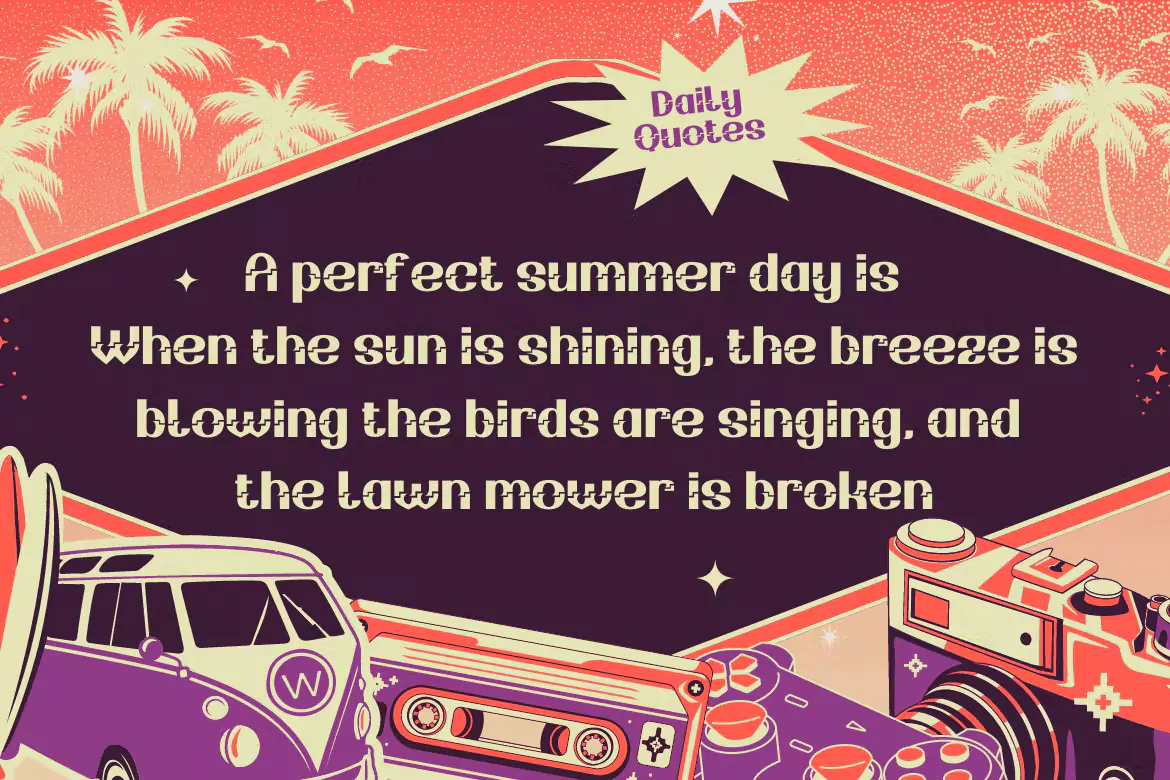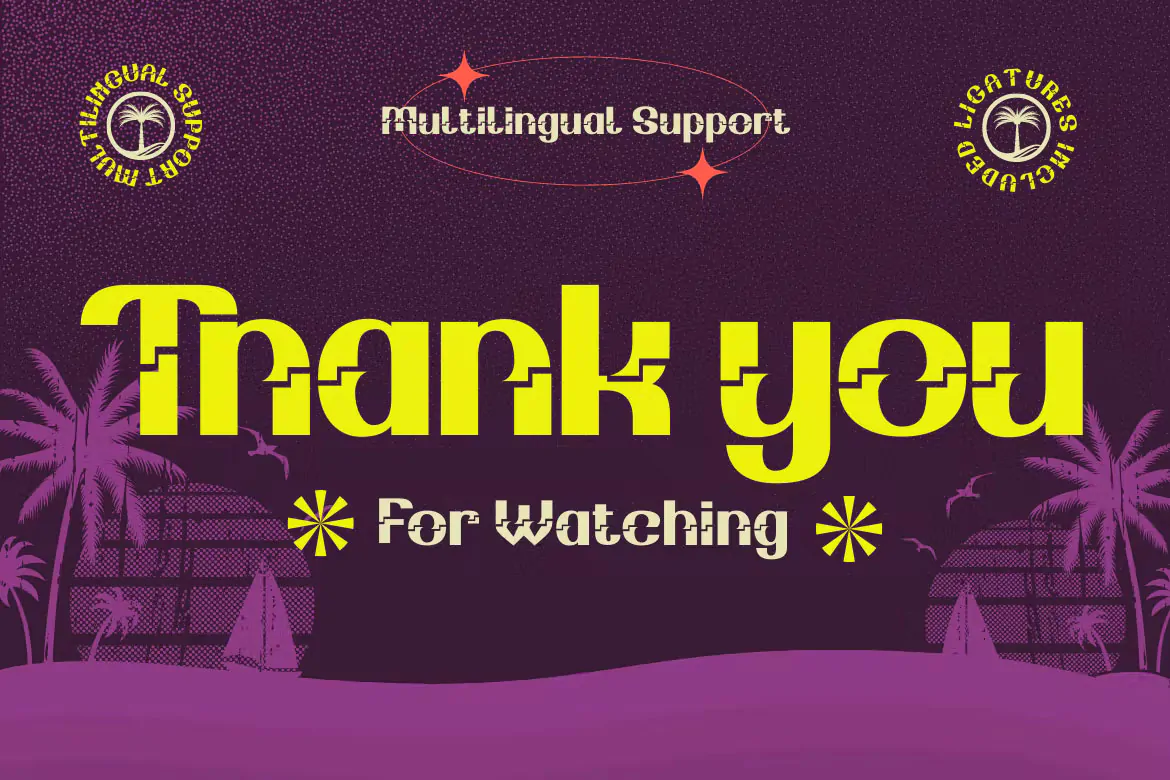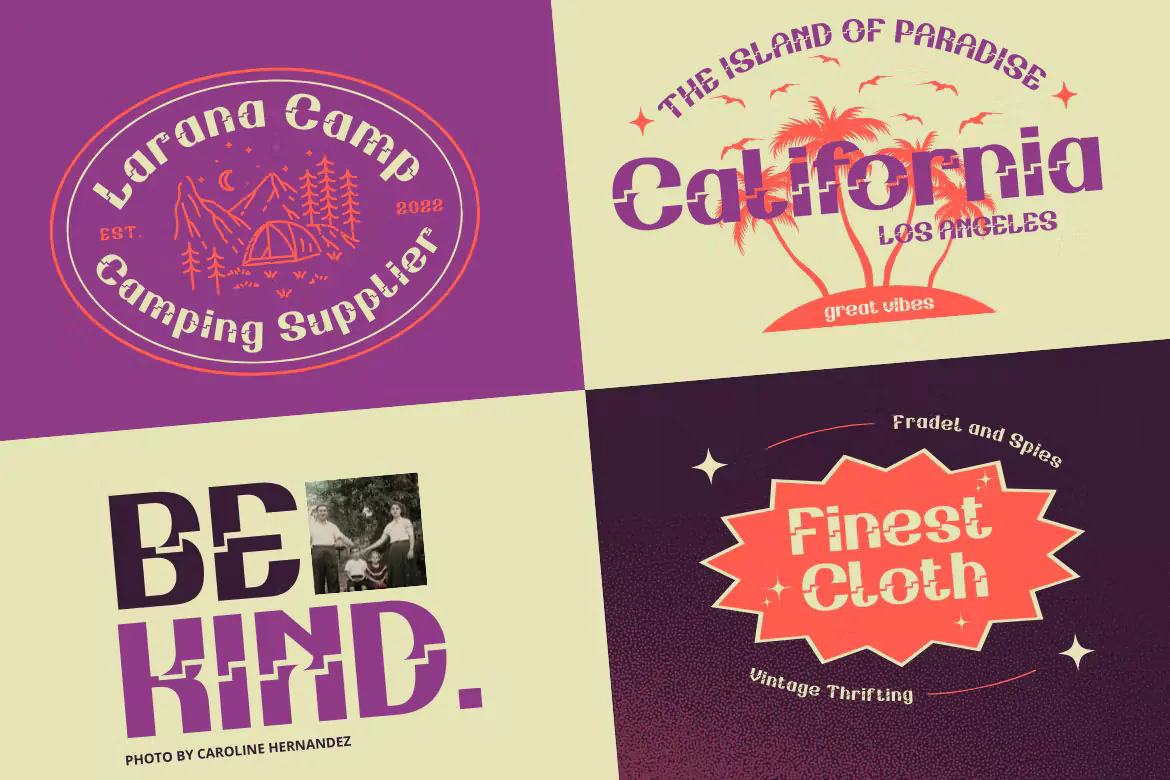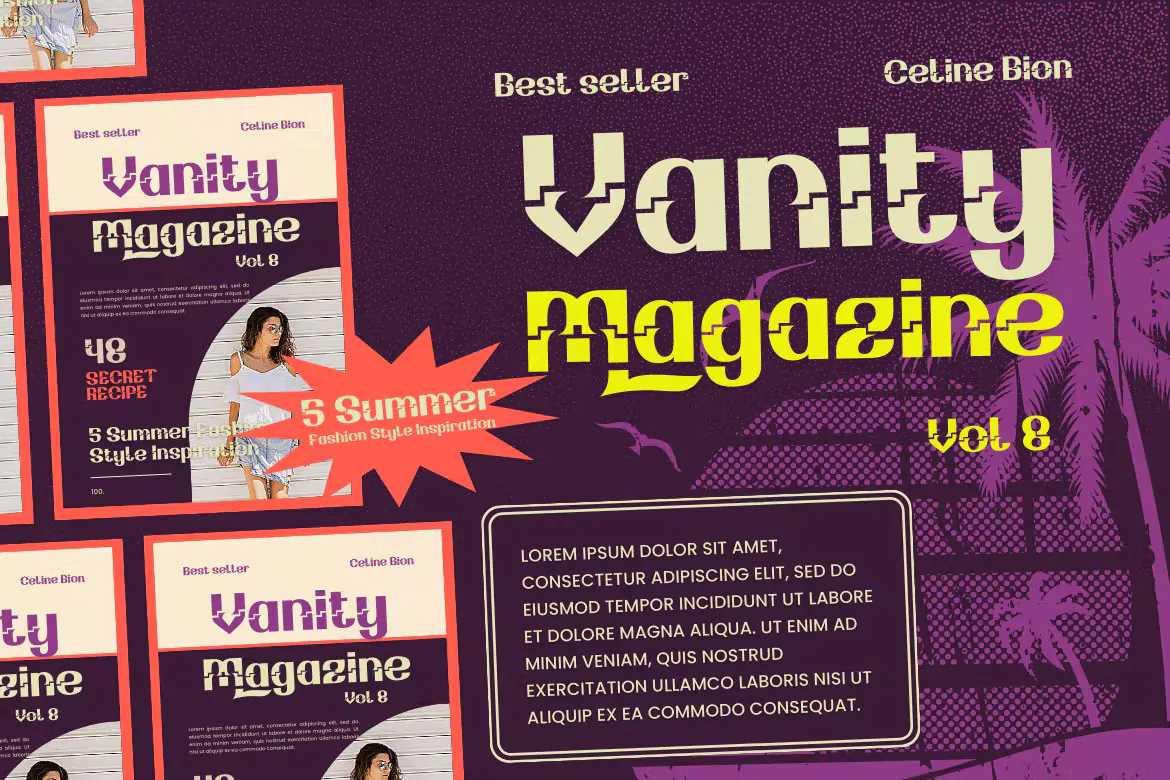
فونت کلاسیک گرووی Navuti
فونت کلاسیک گرووی
فونت کلاسیک گرووی Navuti یک قلم فوق العاده زیبای انگلیسی به سبک رترو است که مناسب برای استفاده در طرح و پروژههای گرافیکی مختلف همچون طراحی پوستر، چاپ تیشرت، بسته بندی محصولات، ظروف یکبار مصرف و … میباشد.